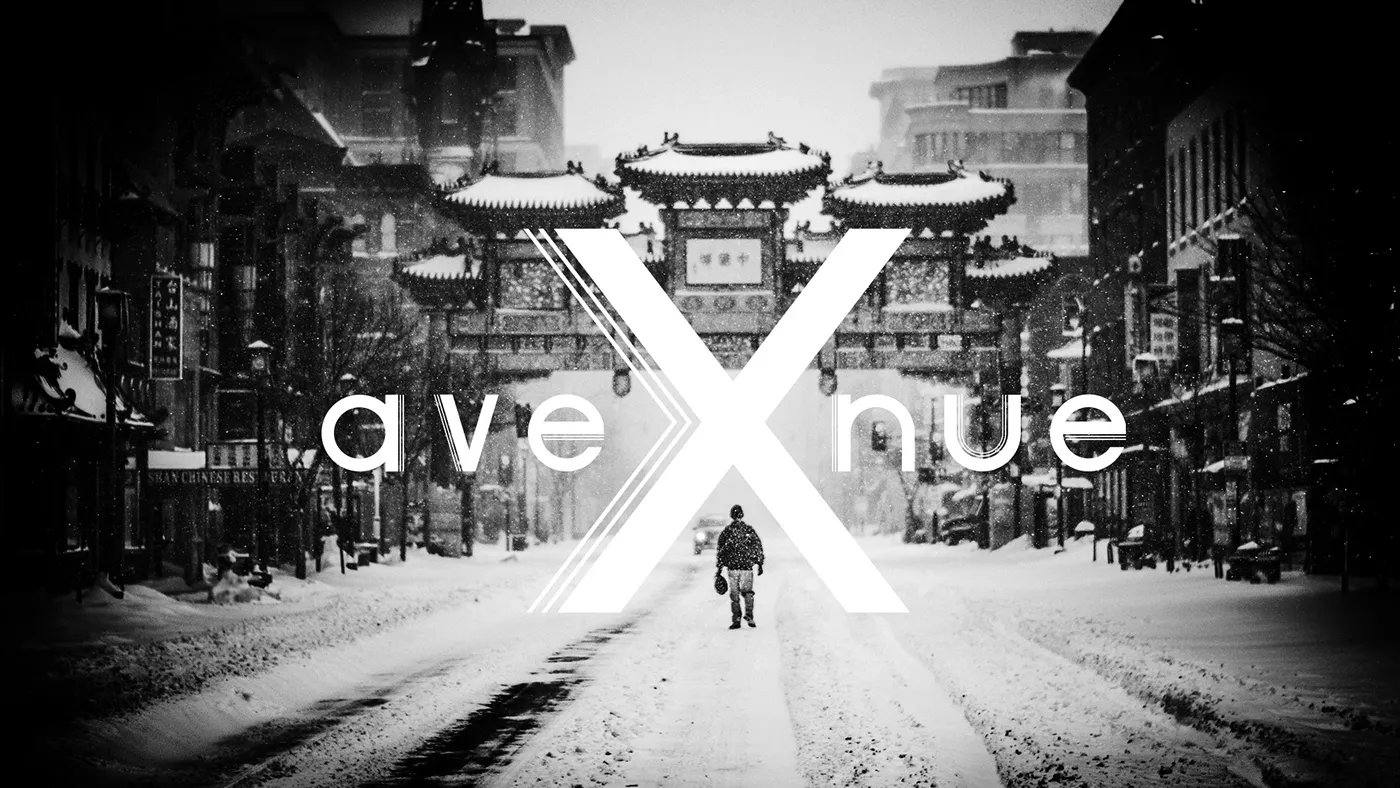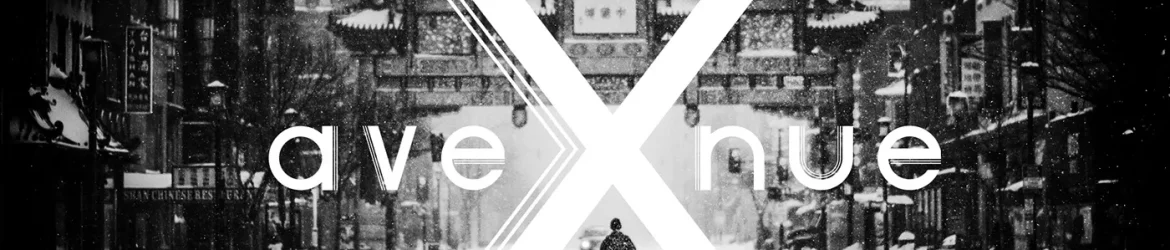
Avenue X Font – Download Grátis
A Avenue X Font é uma fonte de display criada pelo designer Hamilton que oferece características únicas para aqueles buscando destaque visual em sua obra. Como a fonte é liberada tanto para uso pessoal quanto comercial, ela se torna um recurso valioso e acessível para designers e criadores digitais. Esta fonte não apenas impressiona com seu design exuberante e moderno, mas também oferece flexibilidade ao permitir que você personalize ainda mais o impacto visual de seus projetos. Como mencionado na descrição original, é gratuita tanto para uso pessoal quanto comercial, garantindo que todos tenham acesso a essa opção poderosa sem comprometer os termos legais ou estilos. A Fonte Avenue X se destaca em sua categoria de fontes de display pelo seu design fluido e elegante, tornando-a uma escolha ótima para qualquer projeto que deseja chamar atenção. Para aqueles que estão procurando mais opções semelhantes na mesma categoria, há um extenso catálogo de fonts disponíveis no BeFonts. É sempre bom lembrar que a liberdade de usar a fonte é limitada apenas pelos termos legais estabelecidos pelo desenvolvedor da fonte. A Avenue X Font não só oferece uma experiência visual impressionante, mas também um valor inestimável para qualquer projeto que deseja destacar-se na web ou no design impresso.